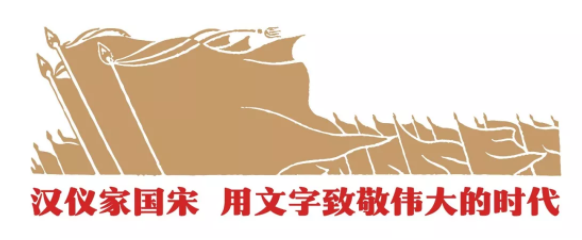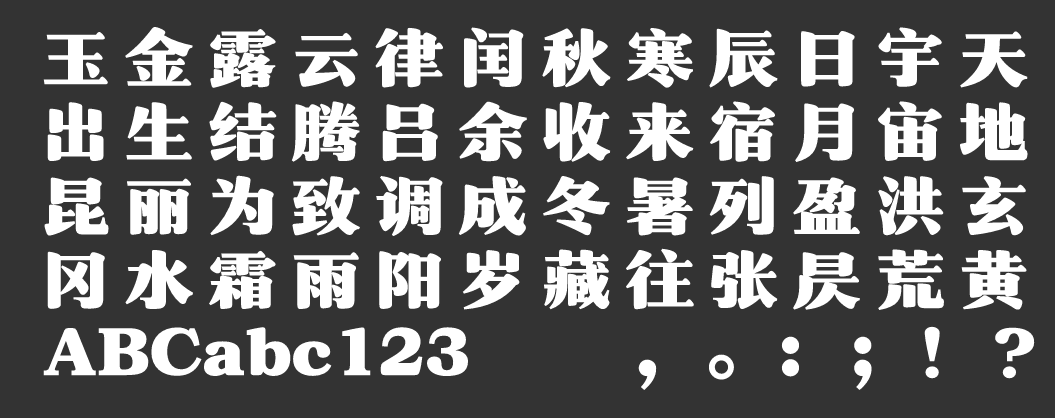
字符集 9169中文简繁 + 拉丁字符
中文字体主创设计 黄珍元
西文字体主创设计 刘嫣然
字体设计团队 汉仪字研工作室
字体设计校对 白云
汉仪家国宋W
汉仪家国宋,是一款具有新中国时代精神的标语字体,他传承了当年美术字的革命气息,圆润饱满的字型与传统严谨的宋体结构相结合,为这款字营造出一种醒目、沉稳、奋进、质朴的气质,设计灵感源于为人民的艺术,最终服务于人民。